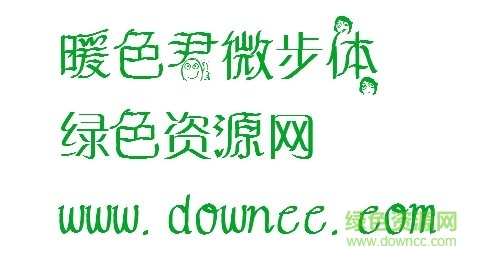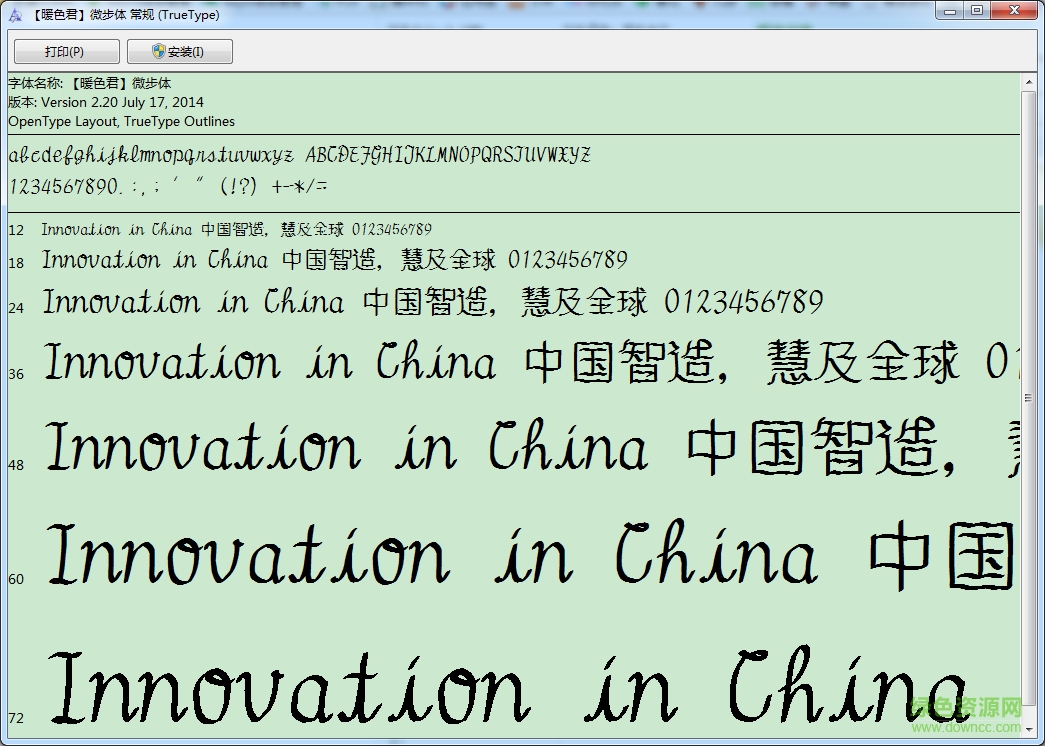
暖色君微步體是暴走梗漫中使用的字?jǐn)?shù)字體,字體有著波浪般的彎曲外觀,給人形散而神不散的視覺享受,讓字體如同被清風(fēng)吹拂變得生動(dòng)活潑起來,喜歡的朋友就來綠色資源網(wǎng)下載吧!
暖色君微步字體線條采用波紋效果,整體效果非常出色,可廣泛應(yīng)用于平面設(shè)計(jì)、廣告設(shè)計(jì)、報(bào)紙雜志、正文標(biāo)題等領(lǐng)域。
適合在設(shè)計(jì)藝術(shù)書信和設(shè)計(jì)藝術(shù)文字繪畫的時(shí)候使用,設(shè)計(jì)一個(gè)文字的時(shí)候采用暖色君微步體能夠提升文字的效果!
暖色君微步體主要展示了原始文字的藝術(shù)性
不需要您自己配置文字符號(hào),馬上獲取一種比較特殊的文字樣式